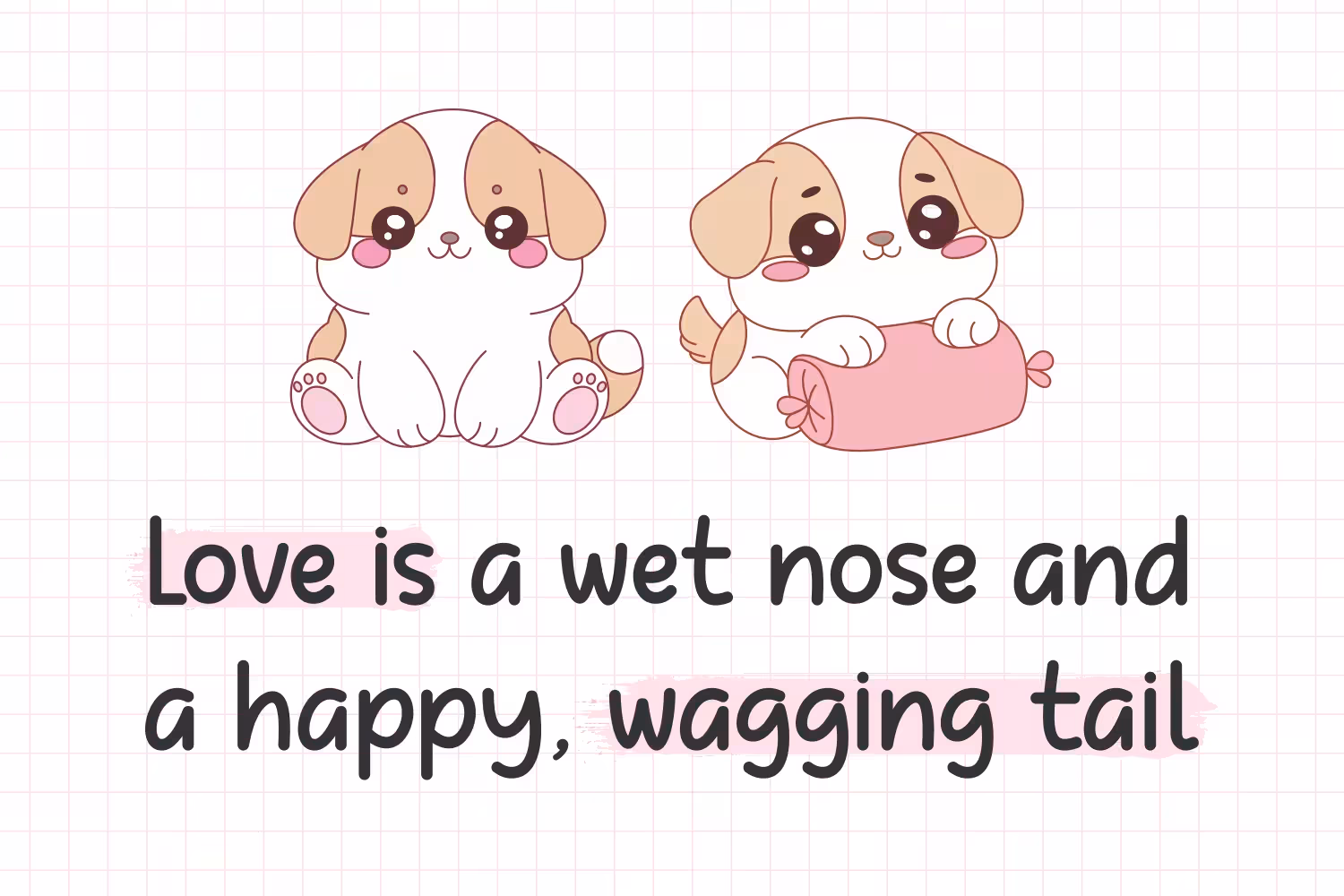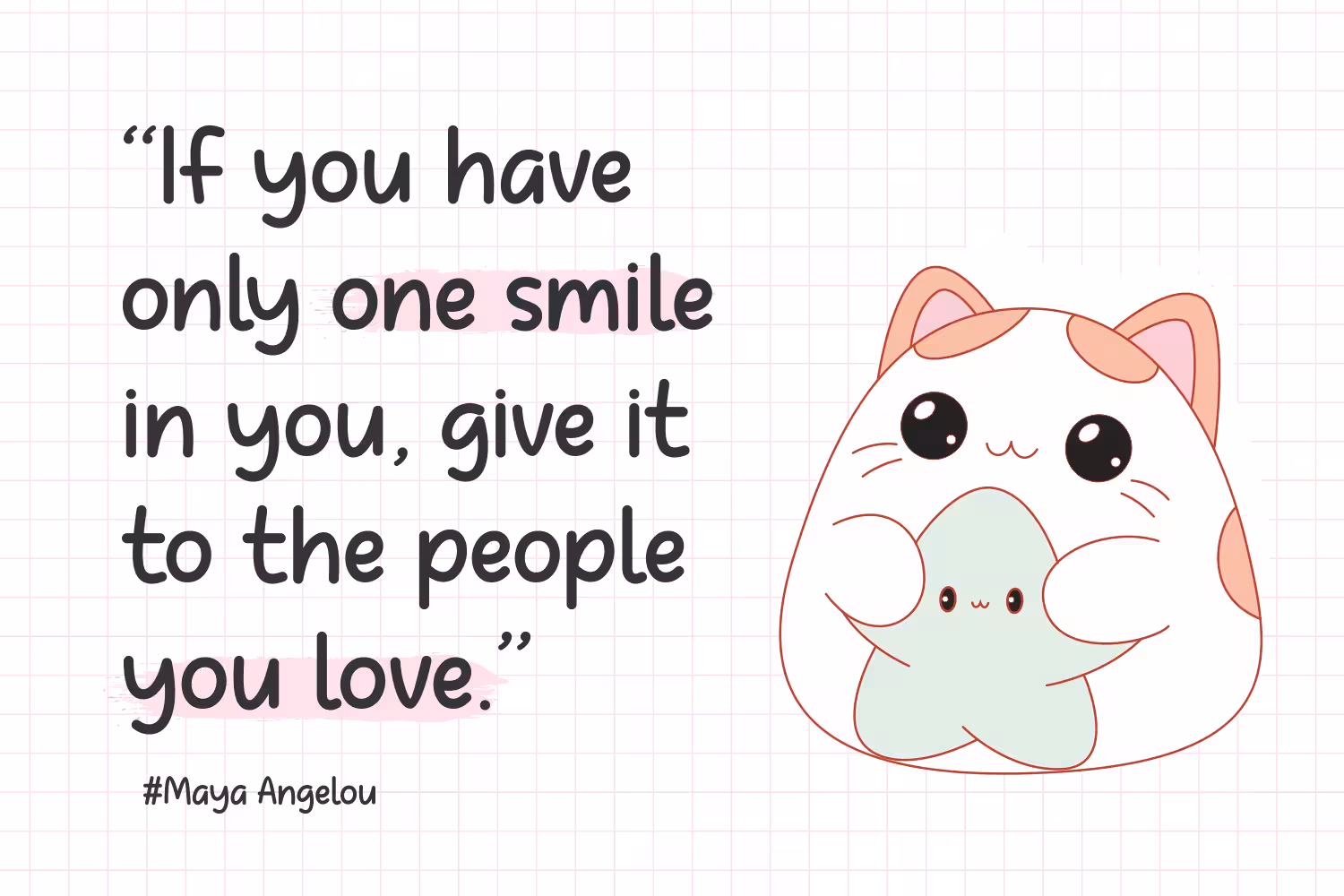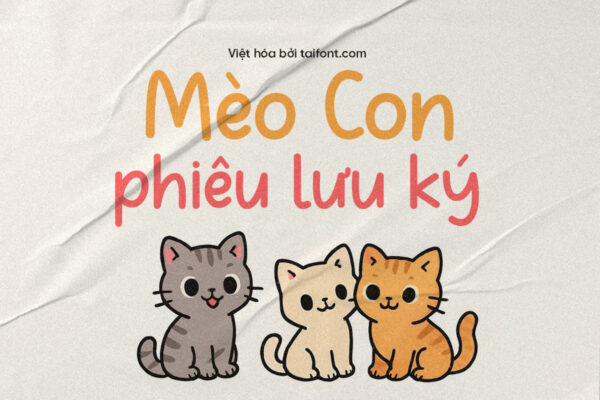
Giới thiệu về Font TF Wonderful Background Việt hóa
TF Wonderful Background Việt hóa là một font chữ viết tay (script font) nổi bật với những đường nét tròn trịa, mềm mại và cực kỳ dễ thương, mang đến vẻ ngoài thân thiện, hồn nhiên và đầy cuốn hút. Font này gợi cảm giác như những nét viết tay tự nhiên, ngẫu hứng nhưng vẫn rất rõ ràng, lý tưởng để tạo điểm nhấn vui tươi và gần gũi.
Với đặc điểm là nét viết tay tròn, dễ thương và phong thái đáng yêu, Wonderful Background là lựa chọn lý tưởng cho các thiết kế muốn truyền tải sự vui tươi, sự thoải mái và sự độc đáo:
- Tạo ghi chú: Hoàn hảo để viết các ghi chú cá nhân, danh sách việc cần làm, nhật ký, hoặc các ý tưởng sáng tạo. Font này giúp ghi chú trở nên sinh động, dễ đọc và thú vị hơn, khuyến khích bạn ghi chép thường xuyên.
- Thiết kế cho trẻ em: Lý tưởng cho sách truyện thiếu nhi, đồ dùng học tập, bảng hiệu trường mầm non, đồ chơi, hoặc các ấn phẩm giáo dục. Font này giúp tạo không khí vui nhộn, ngộ nghĩnh và thân thiện với trẻ nhỏ.
- Thiết kế blog và mạng xã hội: Phù hợp cho các bài đăng trên Instagram, Facebook, hoặc các story cần sự mềm mại và cá tính, tạo cảm giác gần gũi và đáng yêu.
- Thiết kế thiệp chúc mừng: Tuyệt vời để viết lời chúc, lời nhắn trên thiệp sinh nhật, thiệp kỷ niệm, hoặc thiệp cảm ơn, mang lại sự ấm áp và chân thành.
Với TF Wonderful Background Việt hóa, bạn có thể dễ dàng thổi hồn vui tươi, đáng yêu và sự độc đáo vào các thiết kế, tạo ra những sản phẩm không chỉ đẹp mắt mà còn đầy cảm xúc và sức hút đặc biệt.
Font Việt hóa TF Wonderful Background – Font thiết kế truyện tranh